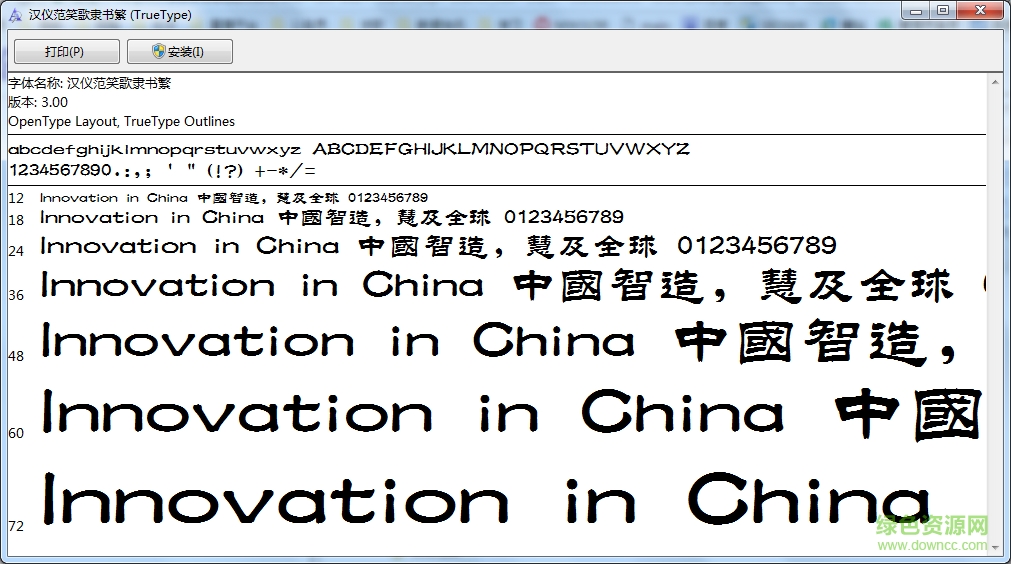
漢儀范笑歌隸書繁字體是一款極具古典風味的繁體字體,這款字體瀟灑舒展,整體效果十分出色,喜歡的朋友歡迎來綠色資源網(wǎng)下載使用!
范笑歌隸書具有魏碑的筆畫筆意,并有篆書的韻味風格,其中的范橫畫是范體隸書特有獨創(chuàng)的筆畫,如同舒展的雙翅,使隸書中的蠶頭燕尾更張揚,更有力度。范橫畫改變了千百年來隸書的蠶頭燕尾的程式寫法,整個字體風格剛柔相濟,瀟灑舒展,具有很強的裝飾性。此款字體適用于書籍、畫報的主副標題和個性品牌設計推廣等環(huán)境。